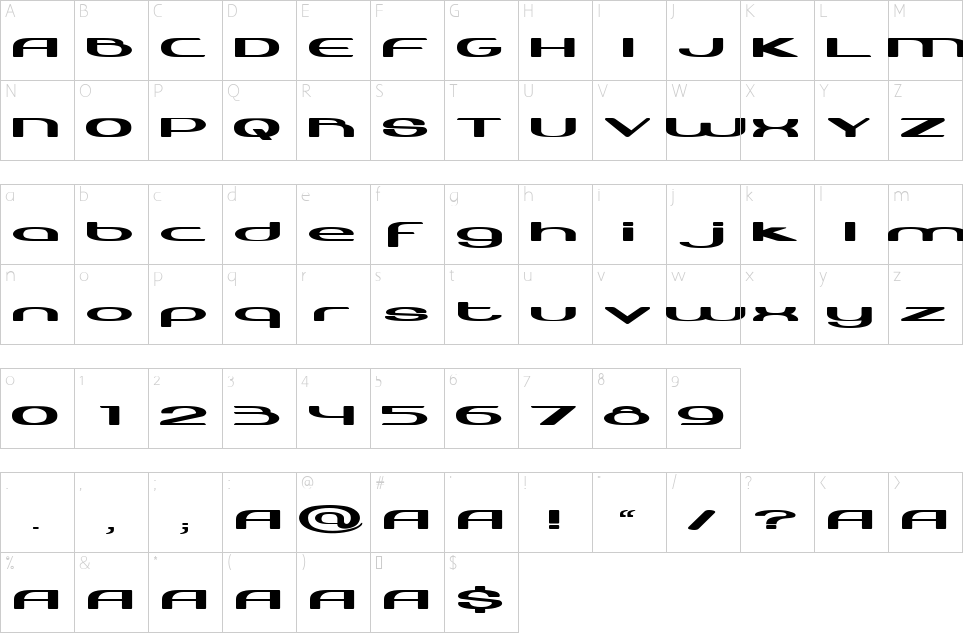
A Harabara Neo é uma elegante fonte que se encaixa perfeitamente para uso em projetos digitais variados. Desenvolvida pelo designer desconhecido Harabara, a fonte oferece um equilíbrio entre modernidade e sofisticação, adequada tanto para textos profissionais quanto para design gráfico criativo. Seu estilo minimalista torna-a uma escolha inteligente para qualquer projeto que valorize simetria e elegância. Esta fonte se destaca por seu formato adaptável compatível com Windows e Mac, permitindo-lhe adicionar um toque especial a seus projetos digitais. Com 5.251 downloads desde sua disponibilização, é evidente o quanto os criativos valorizam a Harabara Neo, reconhecendo seu poder de transformar textos simples em verdadeiros atalhos para expressão visual. Quebre as barreiras do básico e adquira a Harabara Neo hoje. Seu design pode revolucionar a forma como você trabalha com fontes digitais.